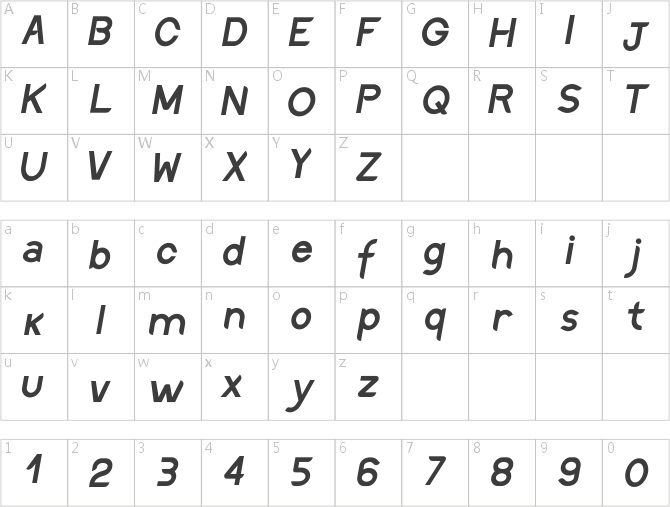
Discreet-SemiBoldInclined
Discreet-SemiBoldInclined介绍
Discreet-SemiBoldInclined字体字库是一款让人赏心悦目、百看不厌的英文字体,适合各类广告和产品包装设计应用,字体大小0.18MB,格式为ttf字体,上传用户是KISEKI,作者/版权方为未知